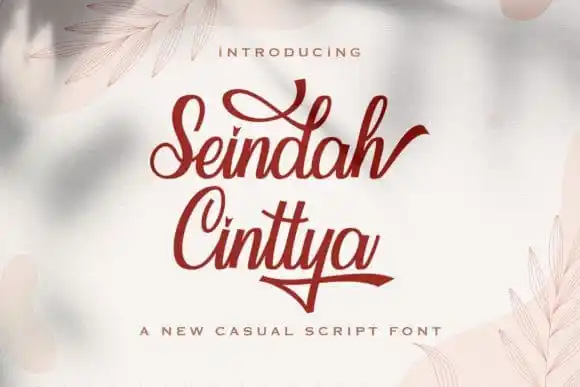
Seindah Cinttya Calligraphy Font – Download Grátis
Introduzimos a Seindah Cinttya Calligraphy Font, uma fonte de caligrafia moderna que oferece alternativas e ligaturas. Esta fonte foi criada e compartilhada pela StringLabs. É uma fonte de escrita à mão finamente projetada para se tornar um favorito verdadeiro. A Seindah Cinttya Calligraphy Font mantém os influentes traços da caligrafia, enquanto transmite uma sensação contemporânea e fresca. Adore o design e elevie seus projetos a níveis superiores! Este é Saulifriend Calligraphy Font, embora estejam associados à mesma casa de criação. O Seindah Cinttya Calligraphy Font oferece um aspecto elegante da caligrafia com uma sensação atual e viva, tornando-o o tipo perfeito para qualquer projeto que valorize a estética do escritor à mão em sua comunicação visual.